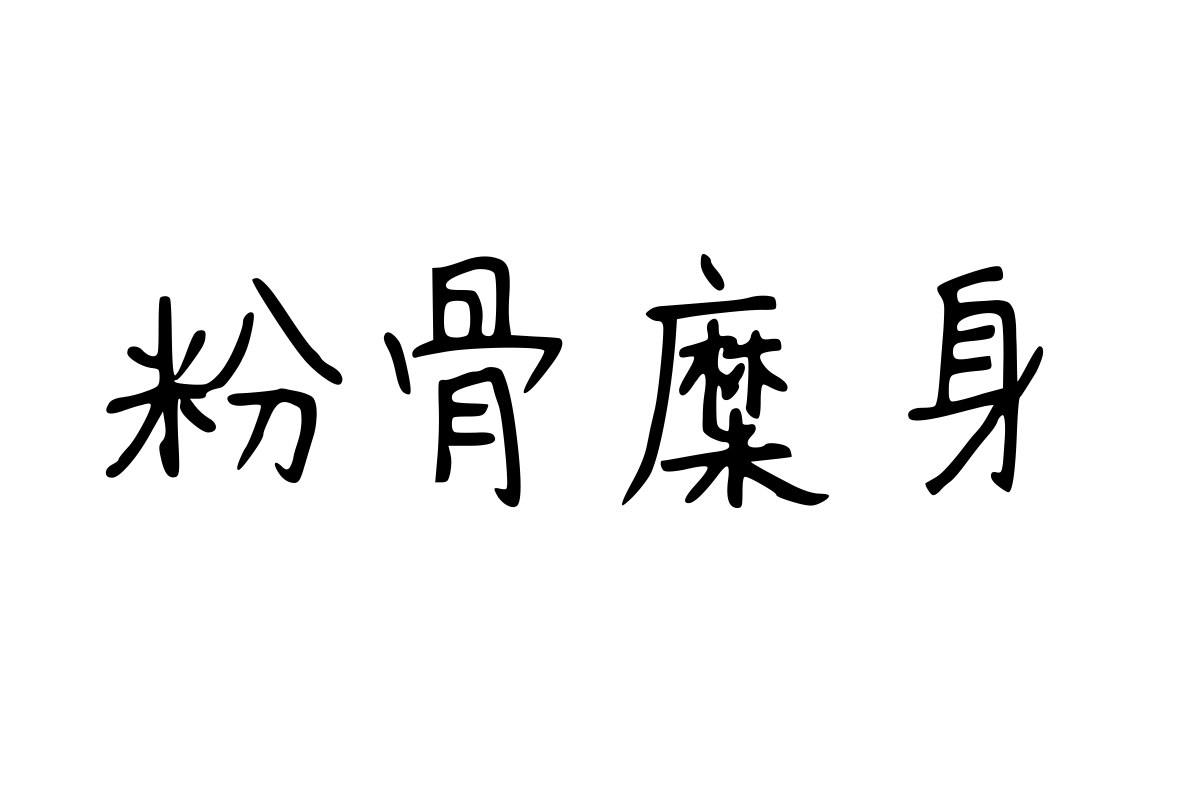
思雨字体-秋水无痕体是一款具有独特美感的字体,其名字来源于中国古典文学中的“秋水共长天一色”这一诗句。这款字体以其流畅的线条和优美的形态,给人以宁静、淡泊的感觉。
秋水无痕体的特点主要体现在以下几个方面:
1. 线条流畅:这款字体的笔画线条流畅自然,没有过多的装饰,给人一种简洁、明快的视觉效果。
2. 形态优美:秋水无痕体的形态优美,线条柔和,给人一种舒适、宁静的感觉。
3. 适用范围广泛:这款字体适用于各种设计领域,如广告、包装、书籍等,能够很好地融入各种设计风格中。
4. 易于识别:由于其独特的造型特点,秋水无痕体在众多字体中具有较高的辨识度,便于设计师进行个性化设计。
总之,思雨字体-秋水无痕体是一款具有独特美感的字体,适合用于需要表达宁静、淡泊情感的设计作品。